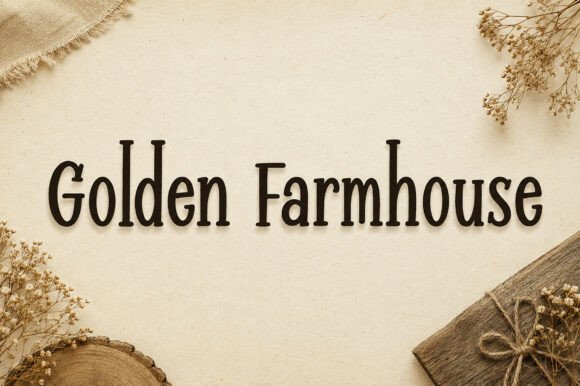
Golden Farmhouse
การค้นหาองค์ประกอบการออกแบบที่เหมาะสมอาจเป็นเรื่องท้าทาย แต่ Golden Farmhouse นำเสนอคอลเลกชันที่โดดเด่นซึ่งช่วยยกระดับงานของคุณได้ทันที
ไม่ว่าคุณจะสร้างผลิตภัณฑ์ POD (Print on Demand) คำเชิญงานแต่งงาน หรือกราฟิกโซเชียลมีเดีย Golden Farmhouse ก็เหมาะสมอย่างยิ่ง